Deze avond heb ik me meer toegelegd op de loops vooral de ascending loop vind ik de moeilijkste. Zie onderstaande afbeelding:
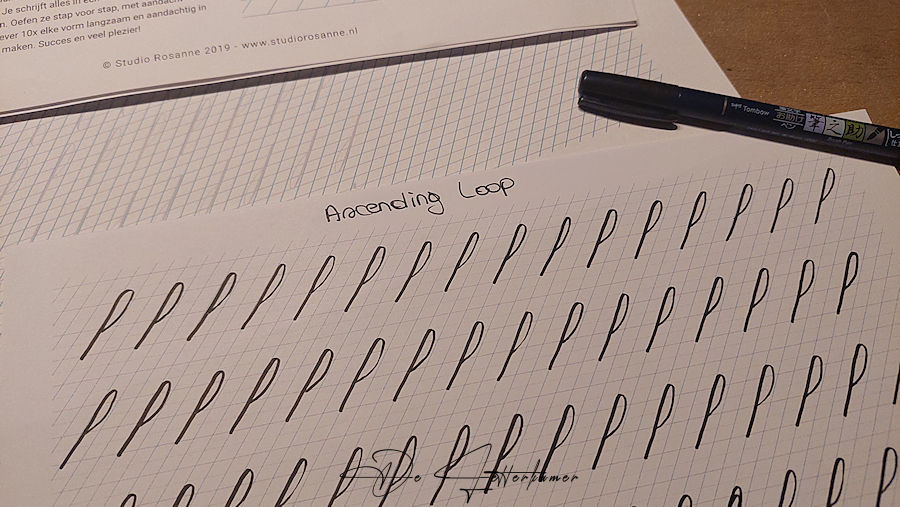
Eerst heb ik mijn hand en het schrijven van letters en woorden een beetje “opgewarmd”, ik moet op de één of andere manier mijn handeling er in krijgen.
Ondertussen heb ik enkele bladeren afgeprint, het nieuwe printpapier van Clairefontaine DCP 90g, het voelt helemaal anders aan dan mijn standaard printpapier van Sylvamo 80g. Veel gladder en ook aangenamer. Benieuwd wat dit gaat geven.
Met een brushpen (Tombow) in de hand schrijf ik mijn 1ste loop die vaak verkeerd loopt, soms stop ik op de verkeerde lijn, de eerste lijn gaat zoals gewoonlijk niet altijd even vlot, strakke lijnen lukt nog niet, ik heb toch nog steeds die kronkels, of ben ik misschien weer te perfectionistisch bezig. Op sommige vlakken kan ik nogal behoorlijk de perfectionist uithangen, niet altijd en gelukkig maar.
Het uitlopen van de inkt is nu veel minder en op dit papier schrijft het een stuk aangenamer. Een volledig A4 formaat heb ik geschreven.
De volgende basisvorm die ik heb geoefend is de descending loop, deze is voor bijvoorbeeld de letter “j”
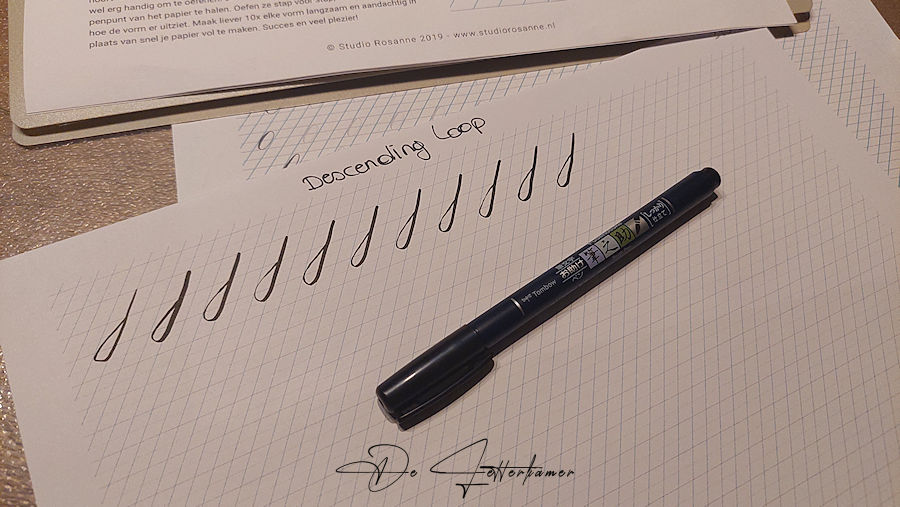
Je ziet de 1ste lijn gaat dikwijls niet goed, op het einde gaat het dan weer veel beter. Ook hier is mijn lijn te hobbelig terwijl ik geen bevend hand heb. Misschien trek ik de lijn te zacht of ben ik misschien te vlug, daarin moet ik mijn snelheid en de druk beter aanpassen, mja dit wordt nog veel oefenen.
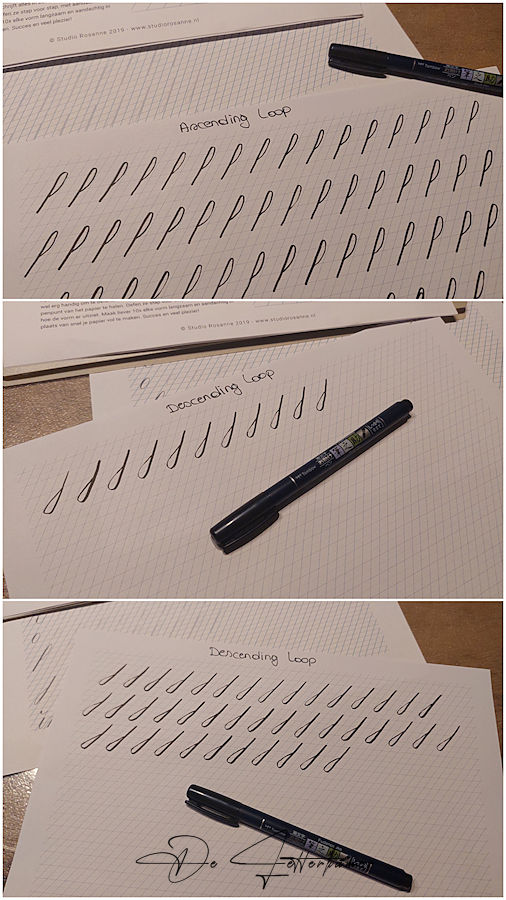
Deze oefening heb ik voor beide basisvormen telkens 2 keer gedaan. Dan ben ik gestopt. Zoals ik eerder heb aan gegeven is een uurtje voldoende tot nu toe toch.